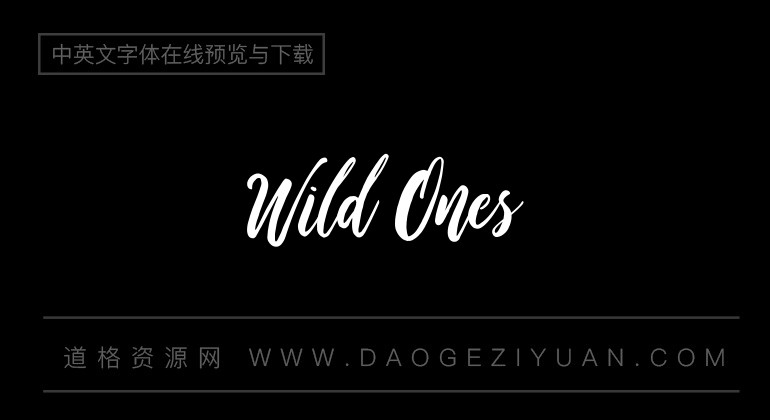
Wild Ones
Wild Ones 字体是一款粗体脚本字体,由 Fontfabric 创作。它具有古典的感觉,但又带有现代感,可以用于各种印刷和设计项目,包括海报、标志、商标、报纸、杂志、书籍、网页等。Wild Ones 字体的特点是丰富的设计元素,包括细节、轮廓、线条等,可以为您的设计提供丰富的灵活性和创造力。
Wild Ones是一款非常不错的手写艺术字体,具有很好的视觉感,适合于文化类的宣传设计、商业类品牌的广告和产品包装设计以及个性化文字排版等较多场景。